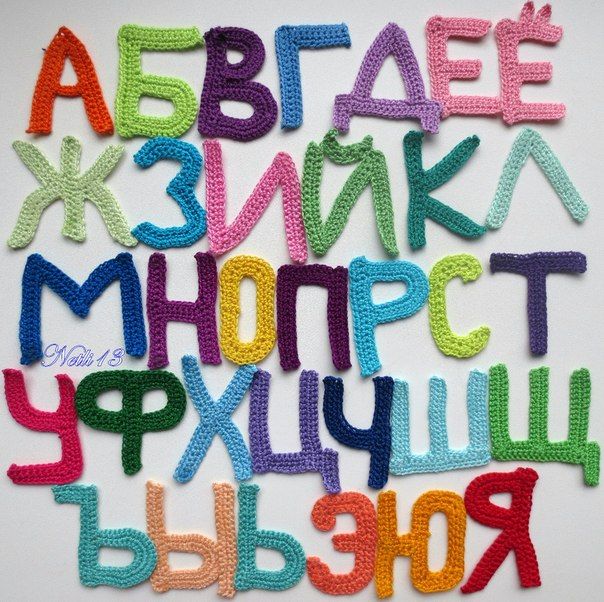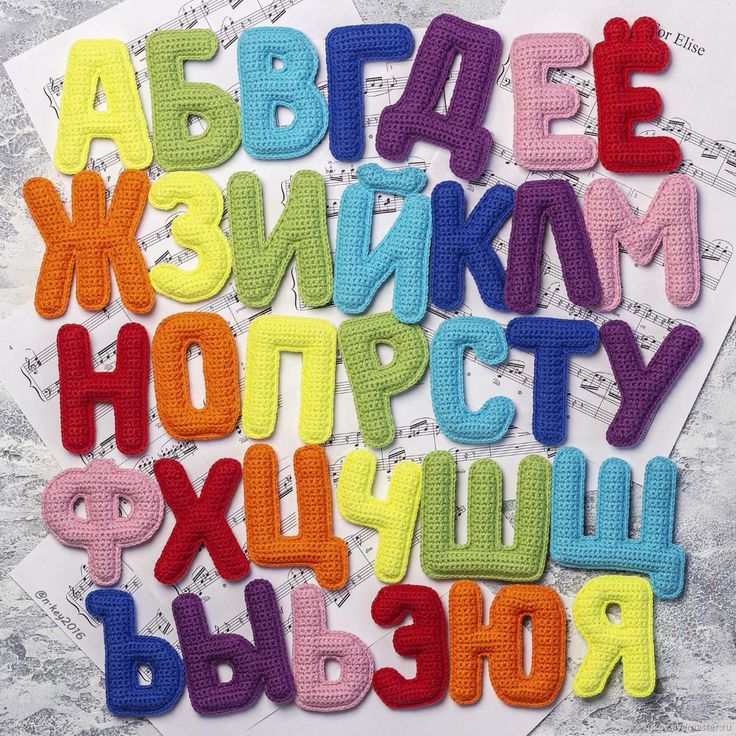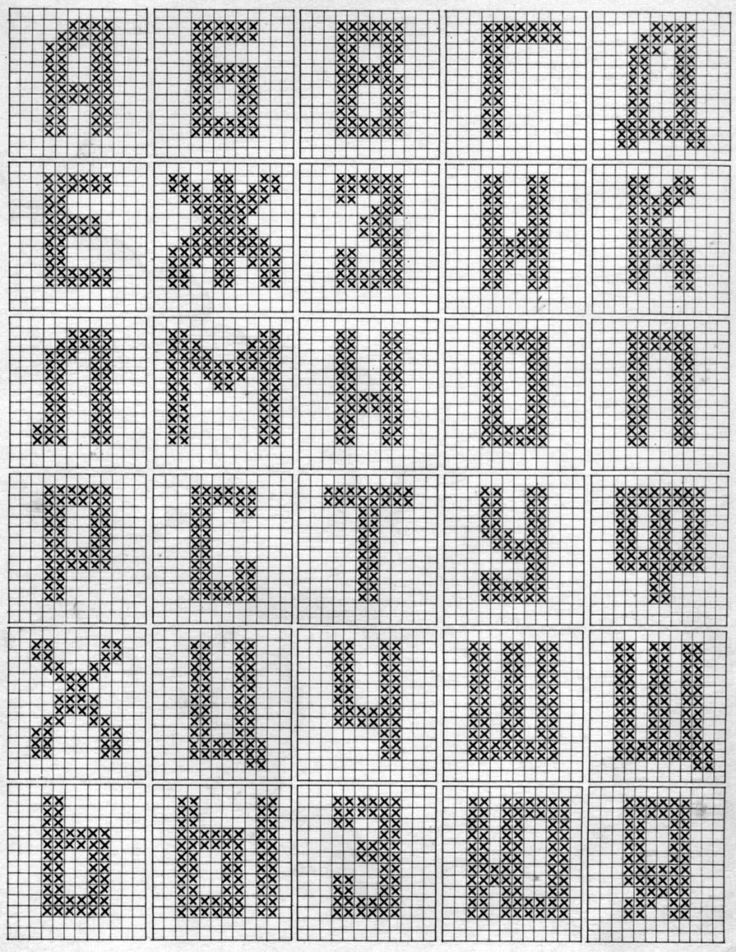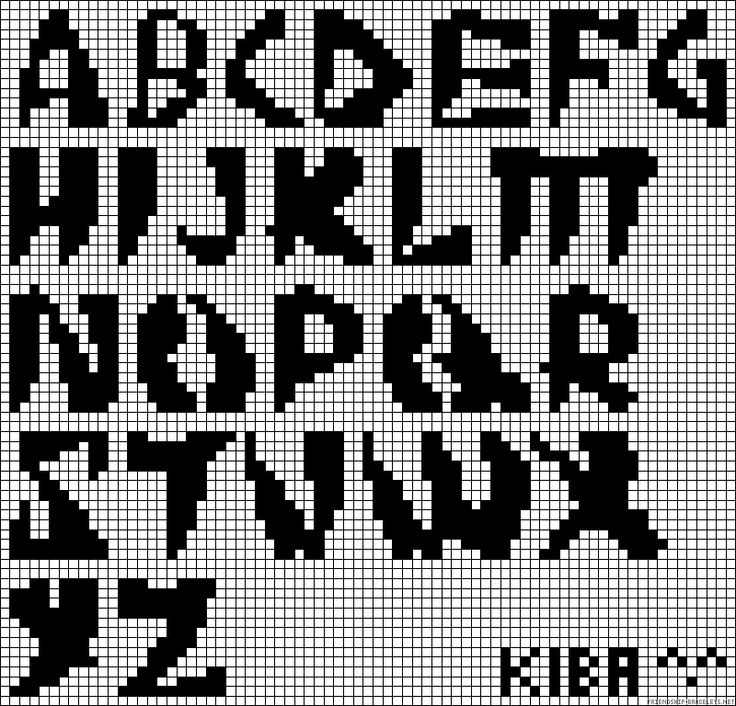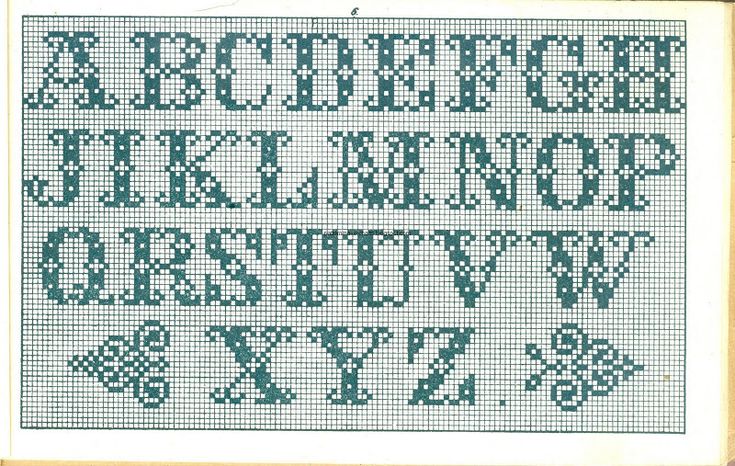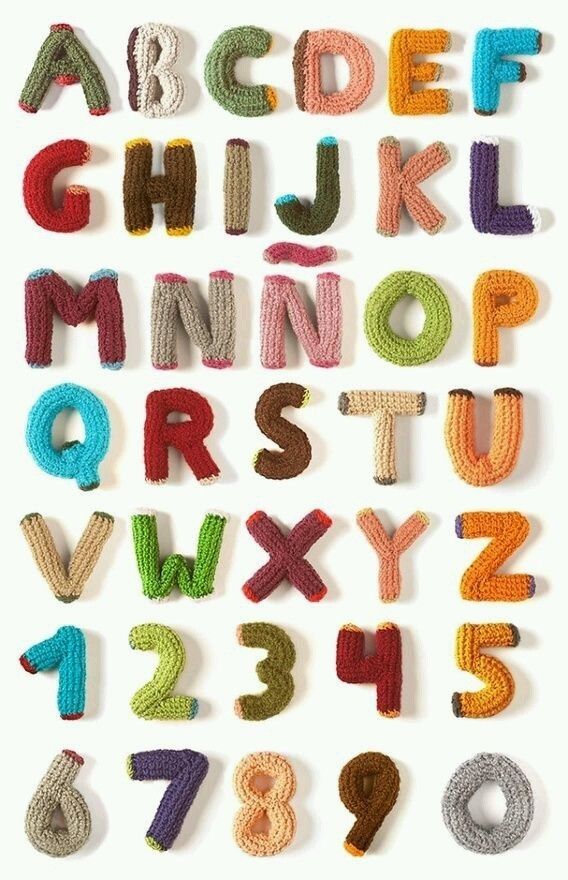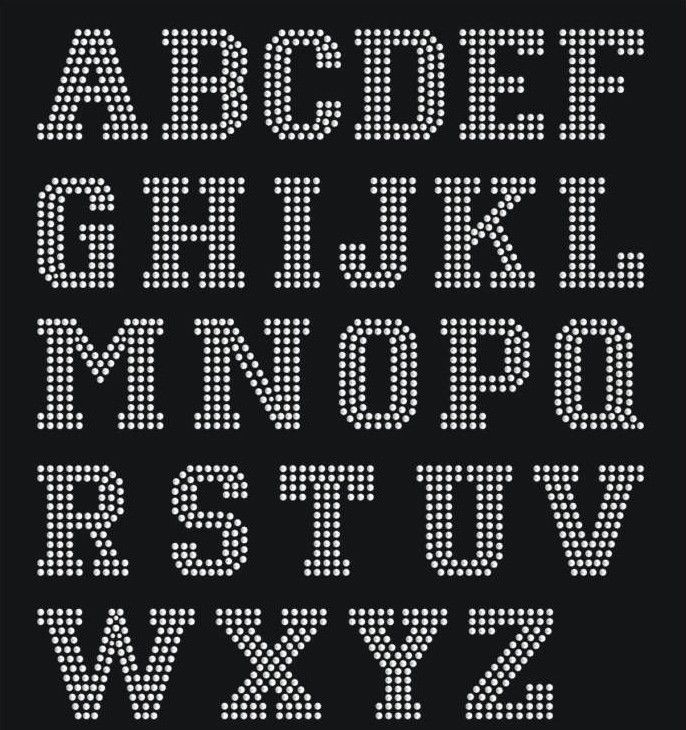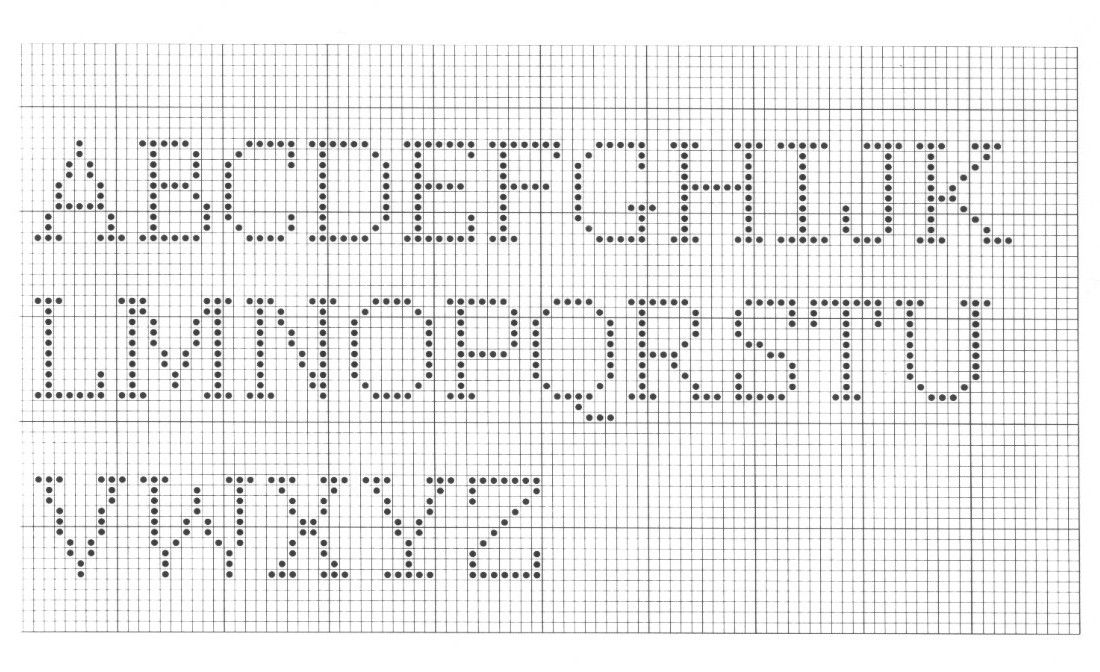
Я хотел, чтобы мои шрифты для вязания соответствовали следующим критериям:
- Точные изгибы (чтобы отразить то, как пряжа образует каждый стежок)
- Стежки, выровненные по сетке (без смещения)
- Правильный калибр (не слишком сжат по горизонтали или вертикали).